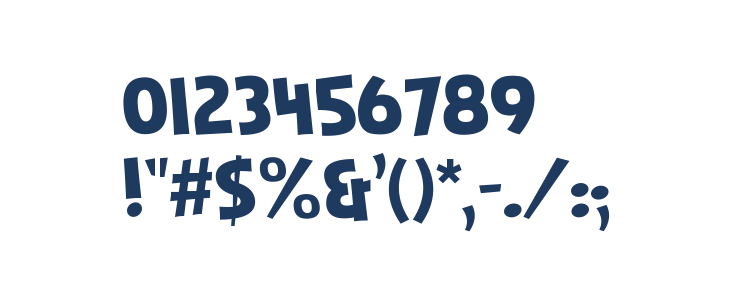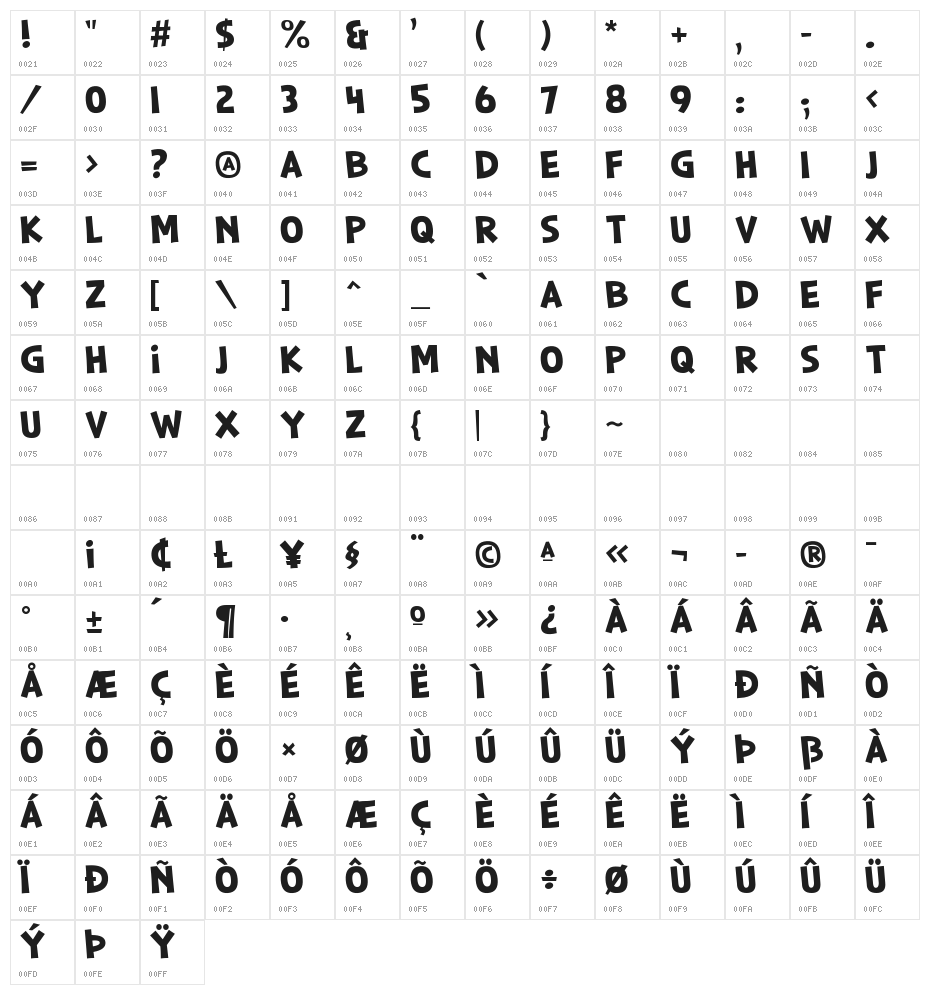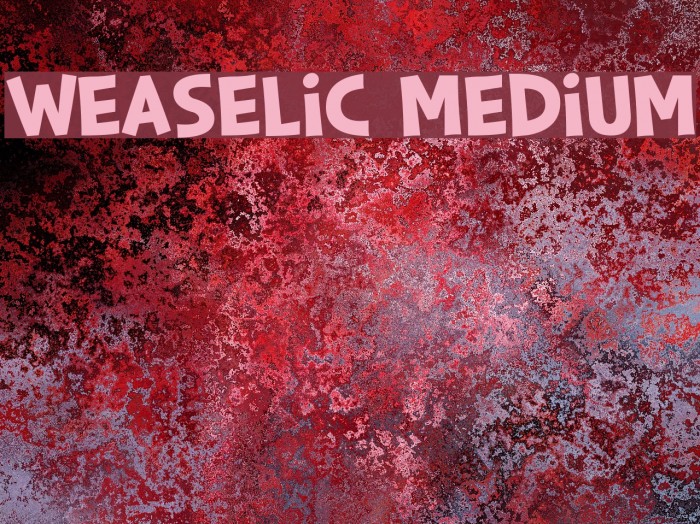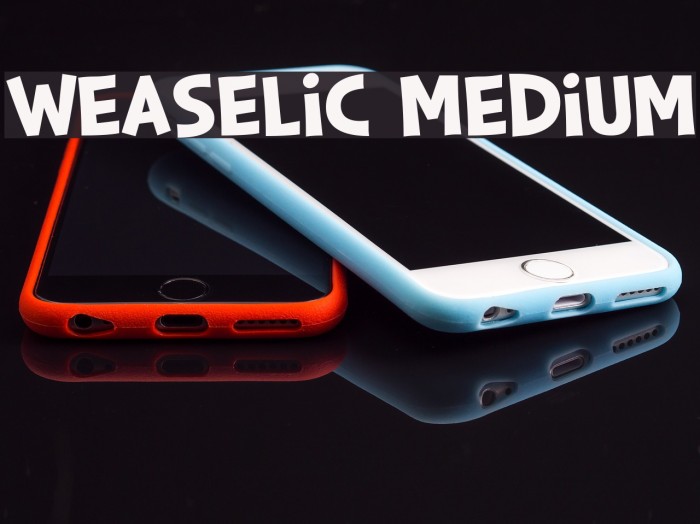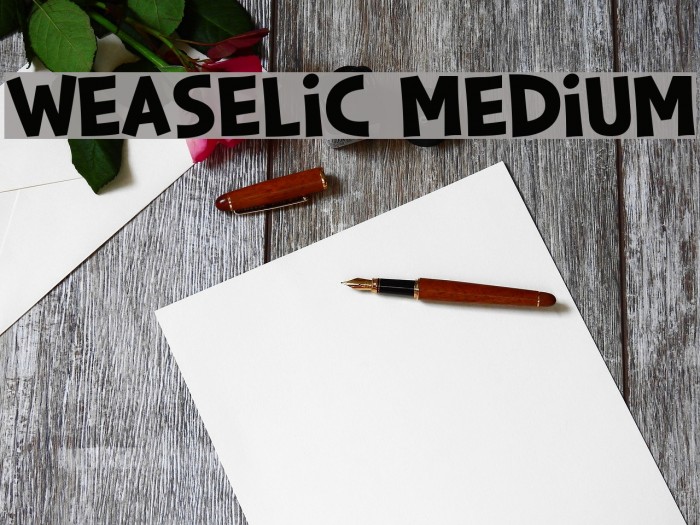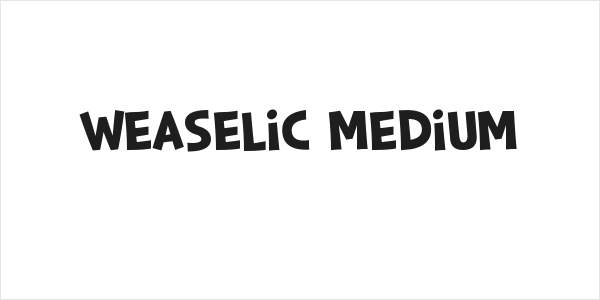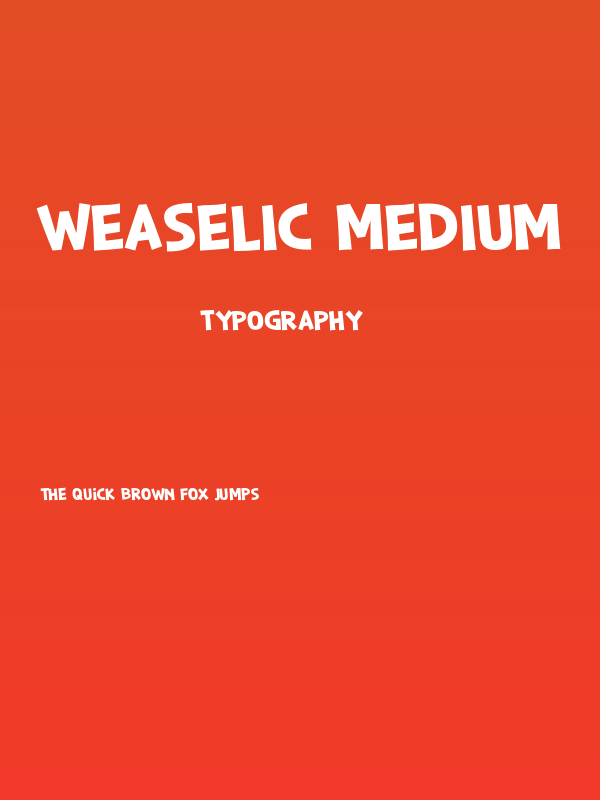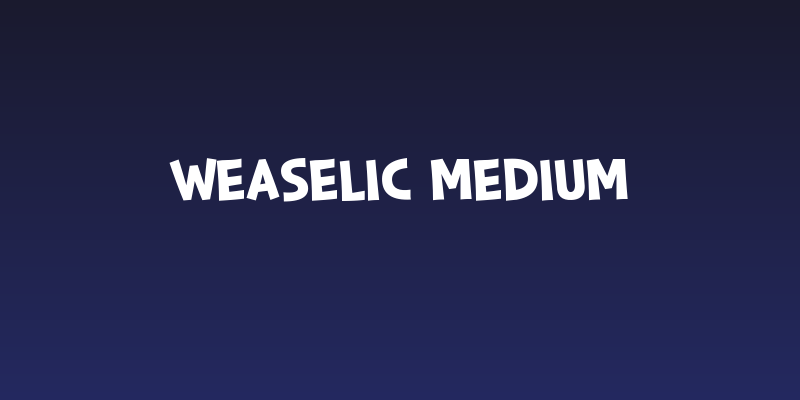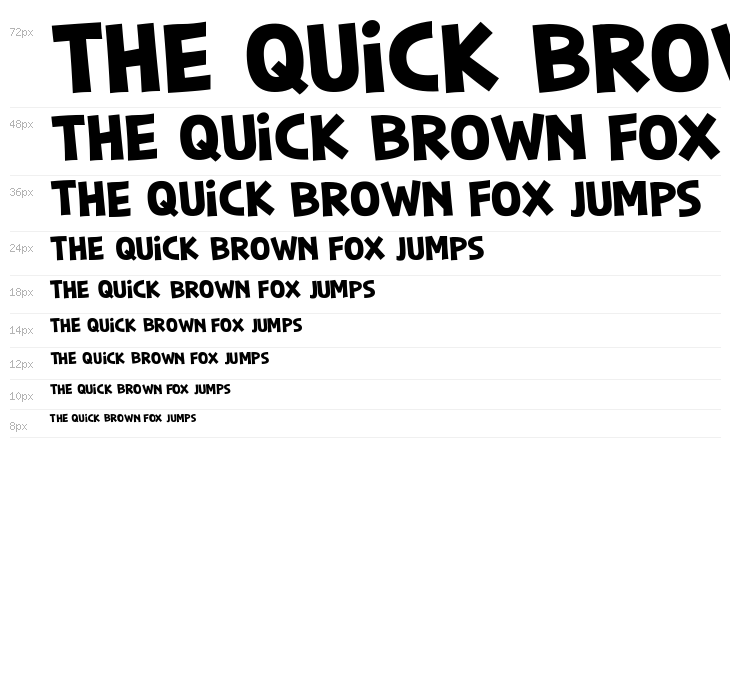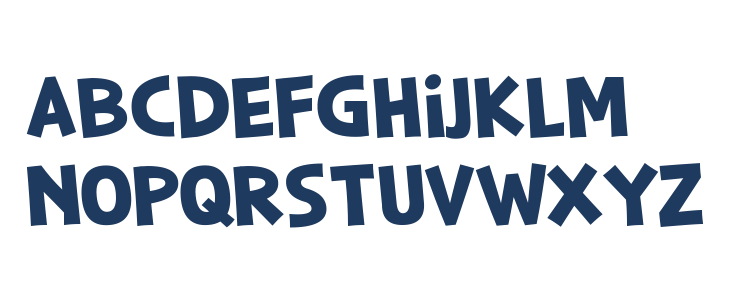
Weaselic Medium Font
| Gesamtstil | Playful, Energetic |
| Anwendungsfall | Headlines, Posters, Branding |
| Vorgeschlagene Projekte | Perfect for children's books, comic strips, playful branding, and eye-catching posters. |